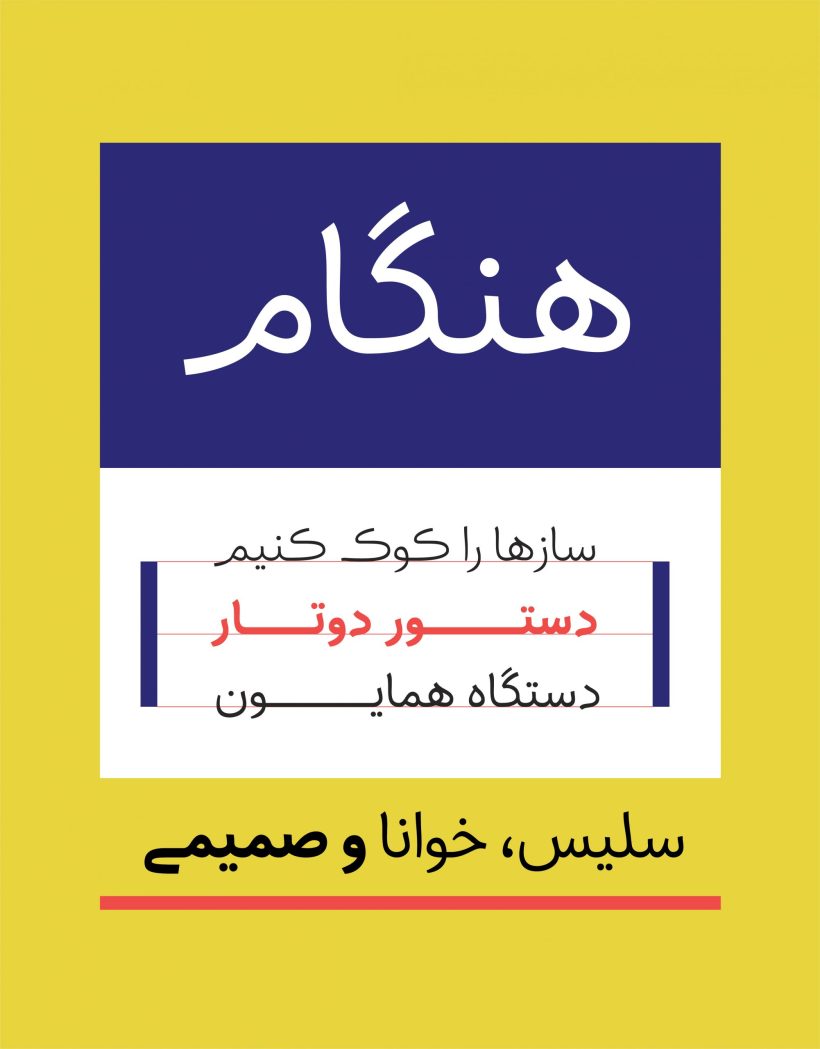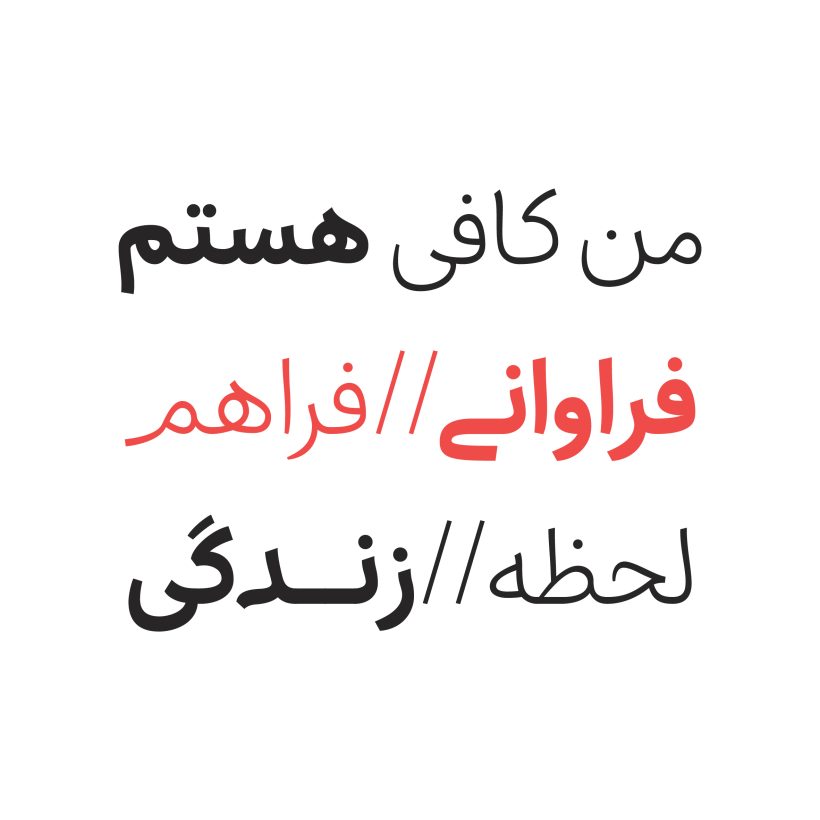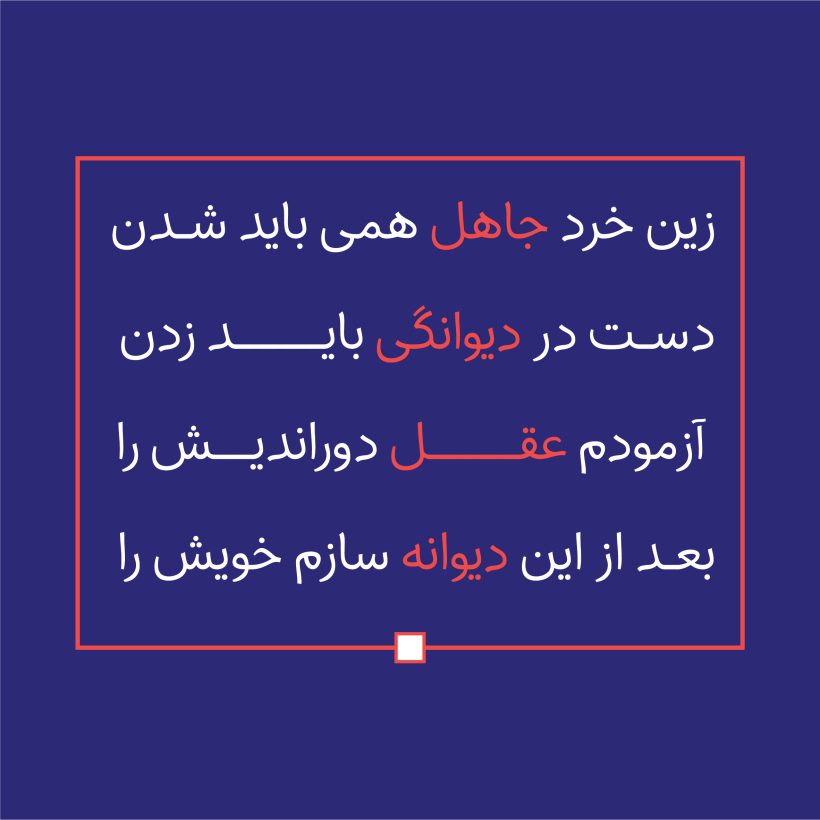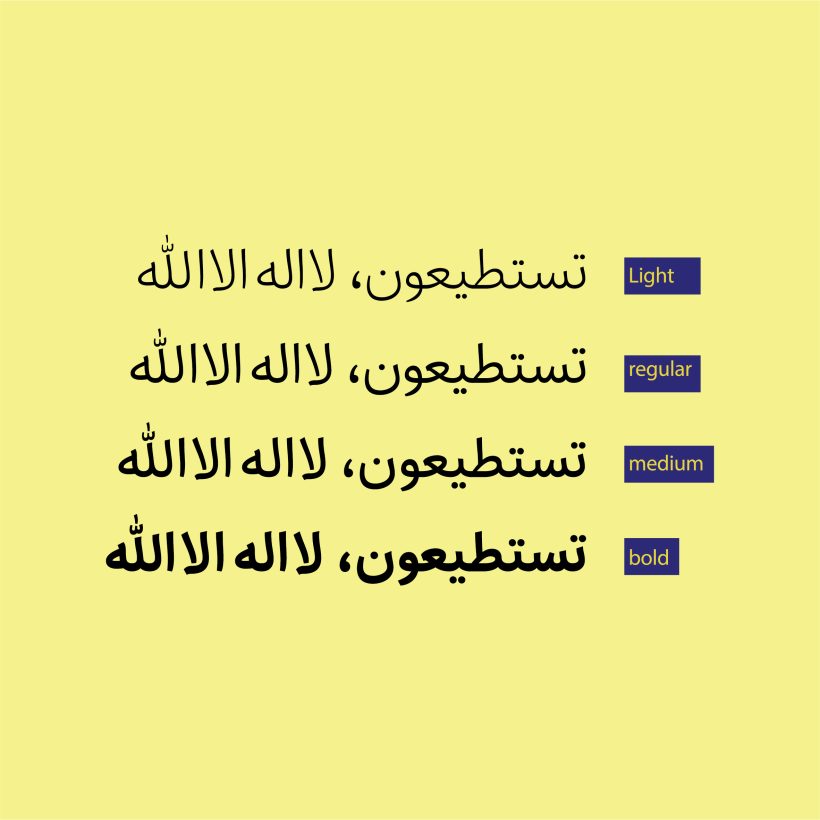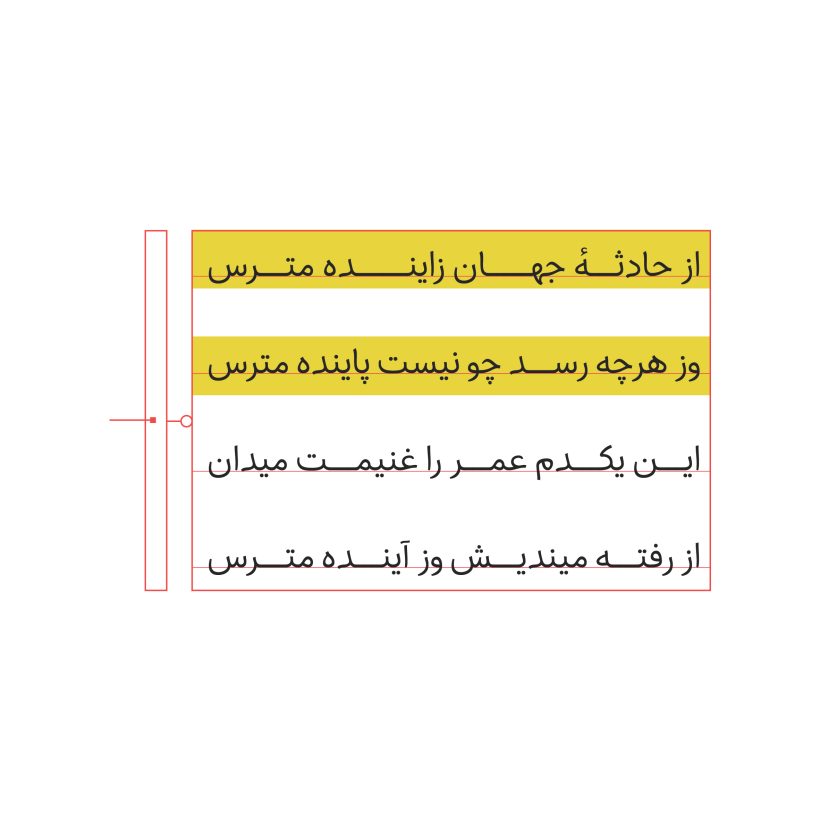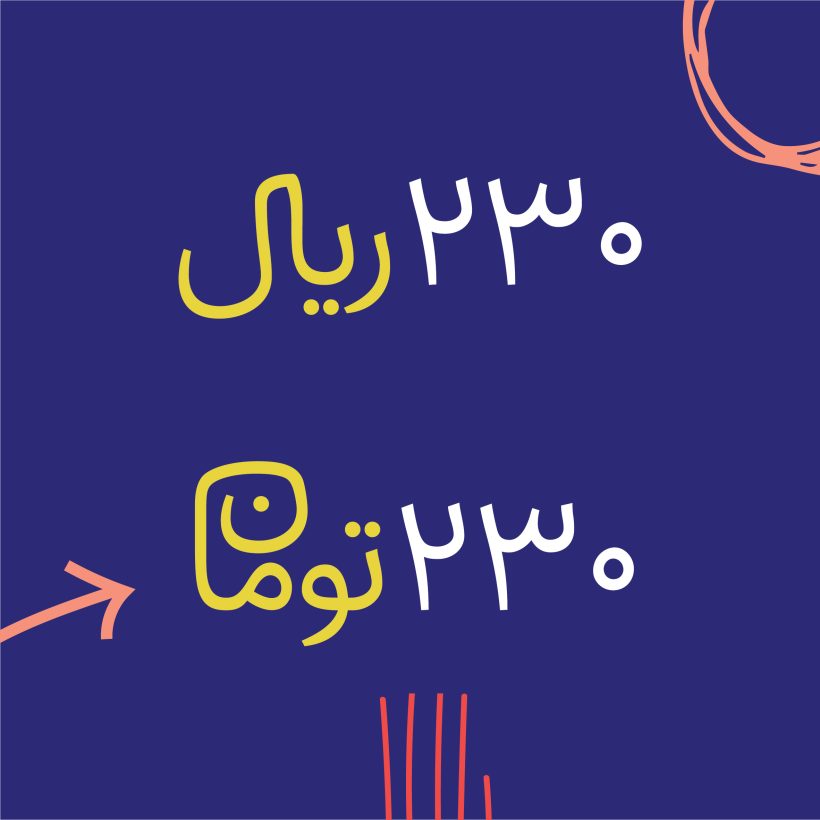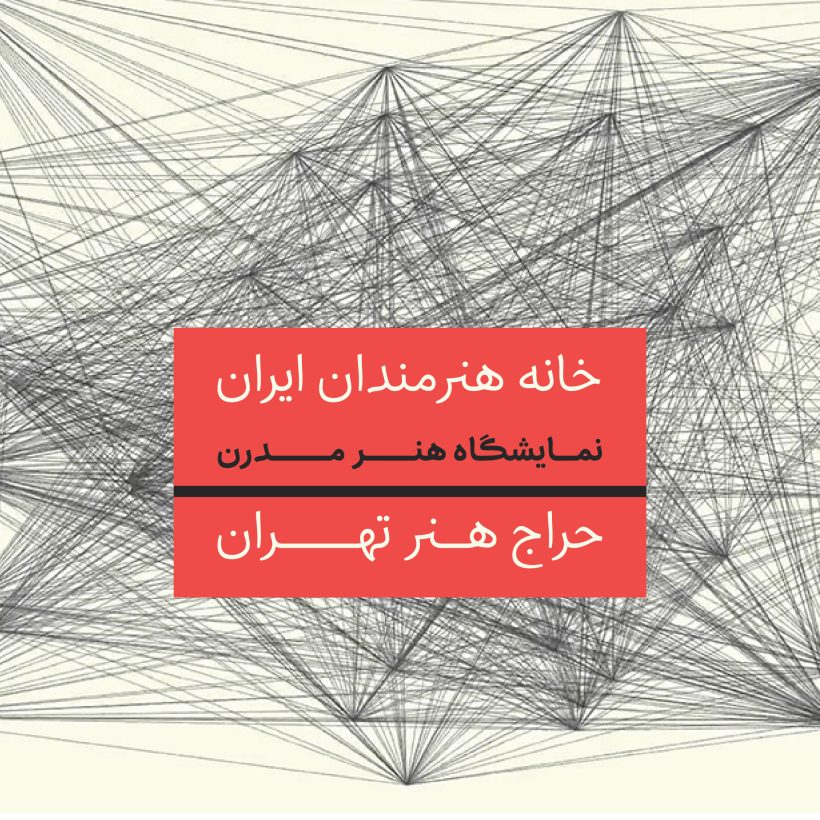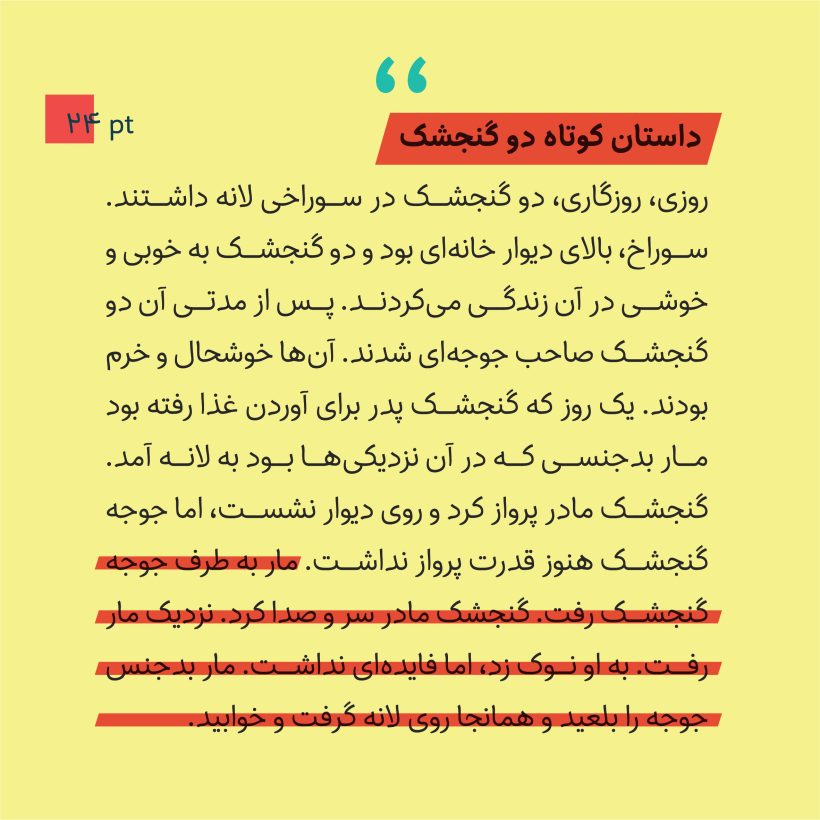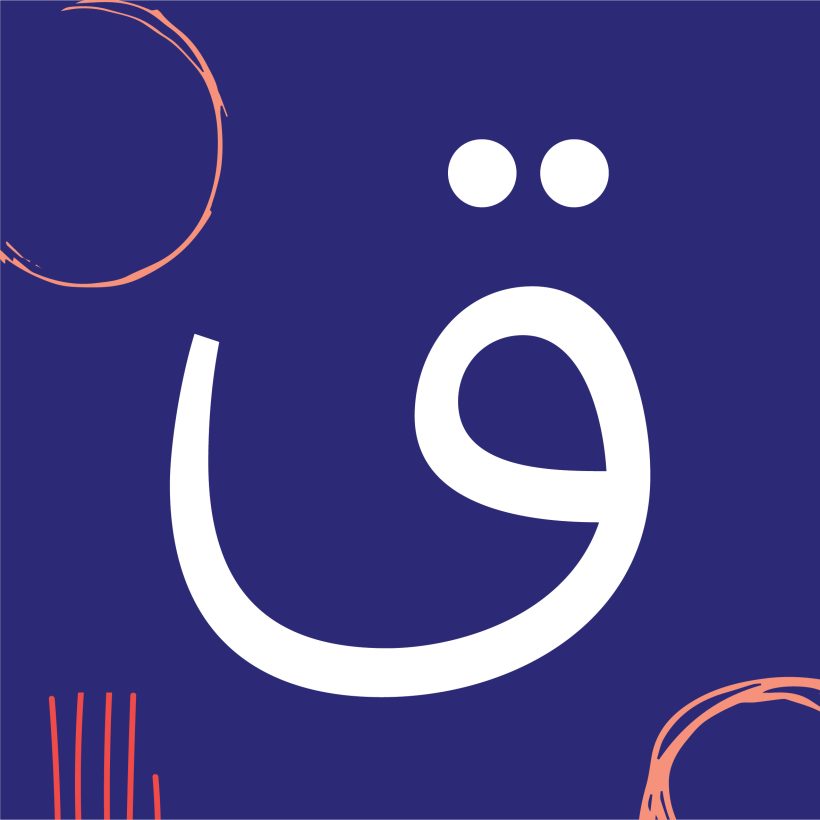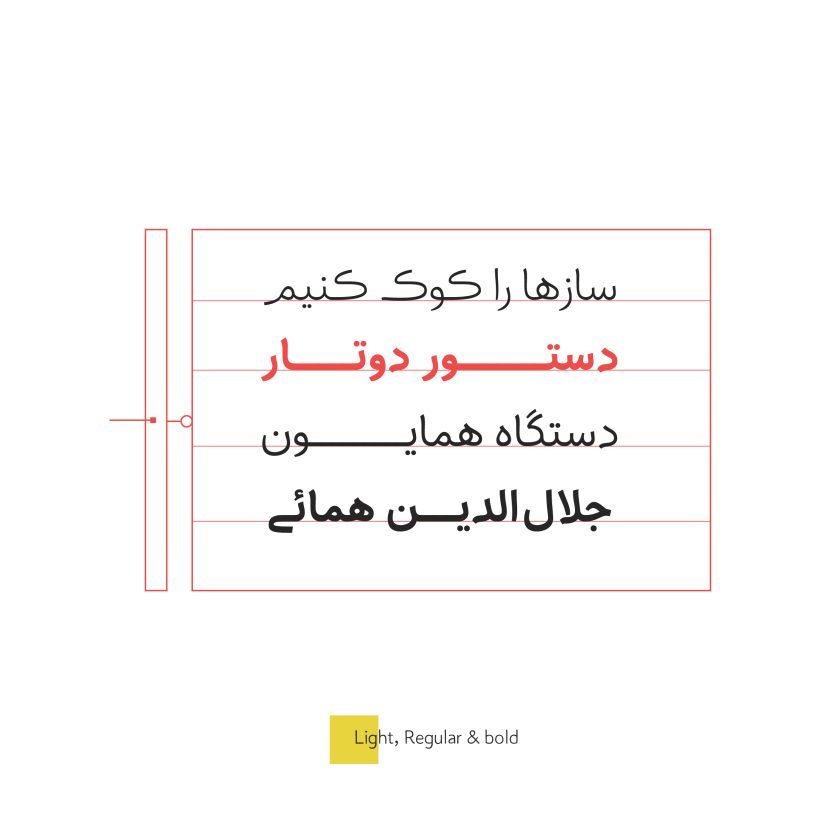
خانواده فونت هنگام
هنگام تایپ فیس متن است و چهار وزن دارد و با ساده سازی و ایجاد دور زیاد در آناتومی خط نسخ شکل گرفته است. تایپ فیس هنگام، دارای لحن سلیس، خوانا و صمیمی است و در آن، گردش های قلم پُر دور، روان و بدون زاویه است. سطح و دور یکی از ویژگی های تاثیرگذار در طراحی تایپ است و متناسب با نحوه و میزان استفاده از آن لحن متفاوتی ایجاد می شود.
کنتراست متعادل پهنا و نازکی حروف از دیگر ویژگی های هنگام است خصوصیتی که سبب ایجاد خاکستری متعادلی در متن و خوانایی حروف شده است. قواعد کرنینگ و اعراب گذاری ها در فونت هنگام اعمال شده است. هنگام دارای لیگیچر و کارکترهای جایگزین است تا برحسب نیاز و برای زیبایی بیشتر به کار گرفته شود.
تایپ فیس “هنگام” توسط معصومه مصلح طراحی شده است.